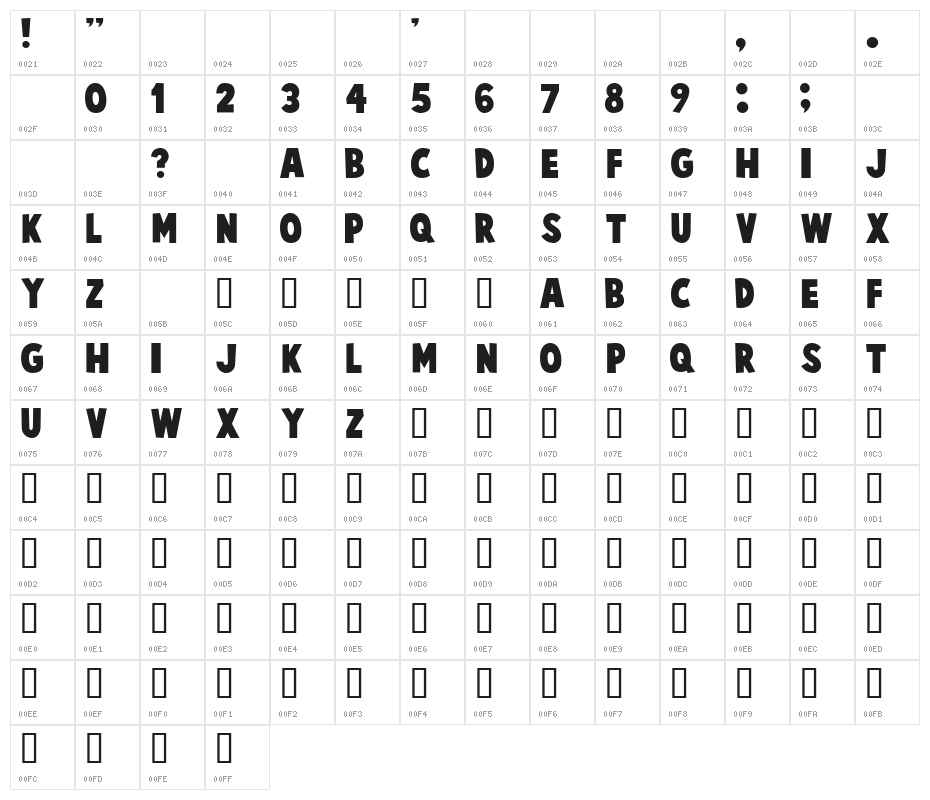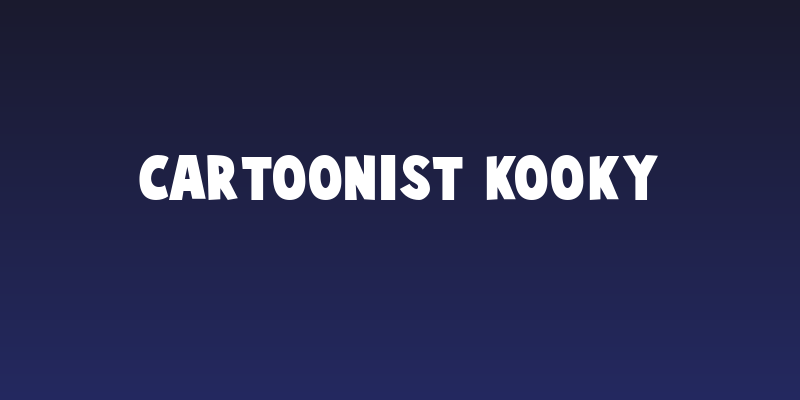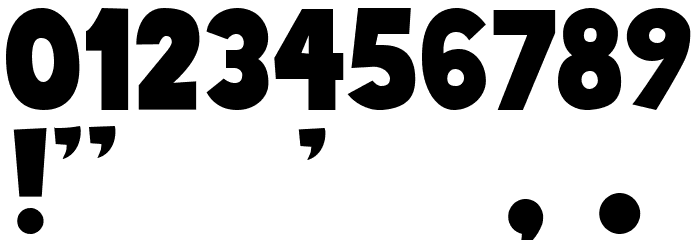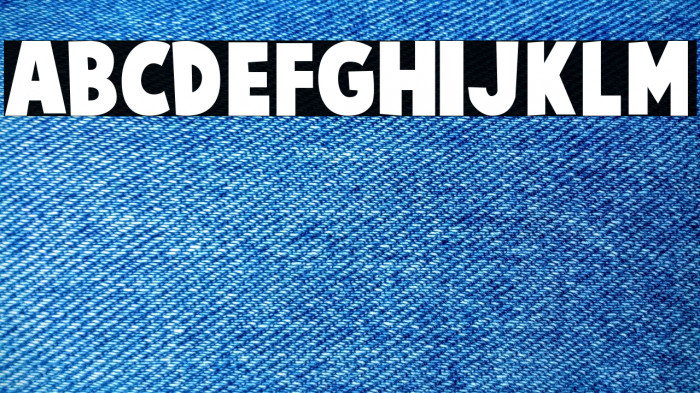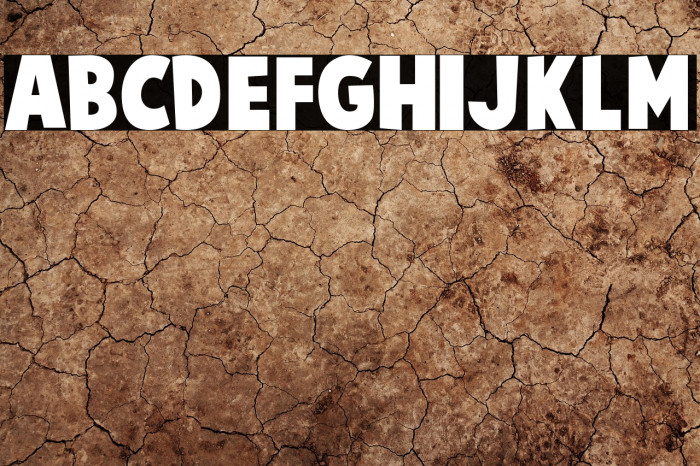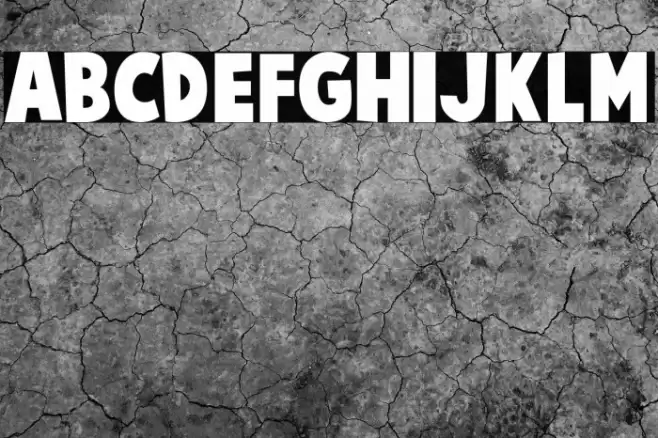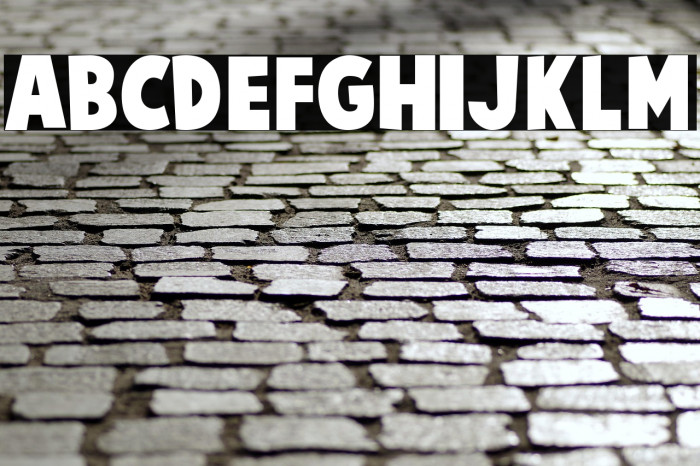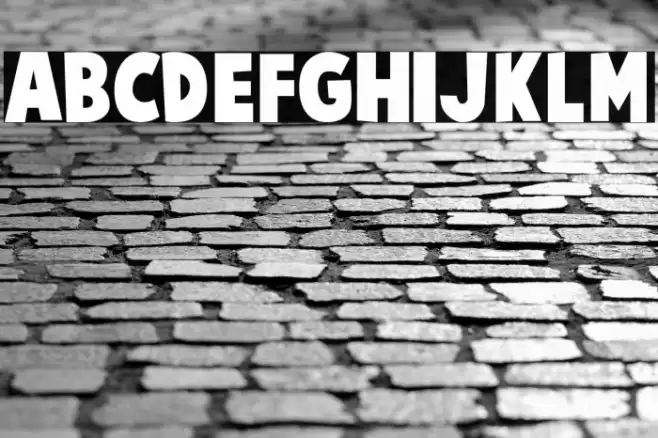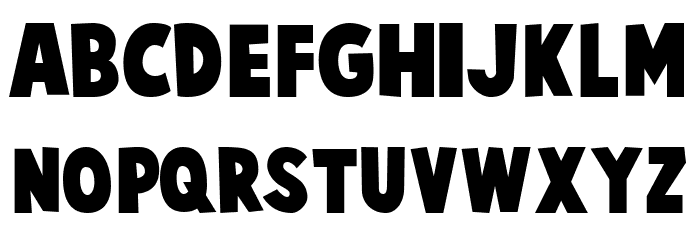
Cartoonist Kooky Font
| Stile generale | Playful, Fun, Whimsical |
| Progetti proposti | Ideal for children's books, comic strips, playful branding, and eye-catching posters. |